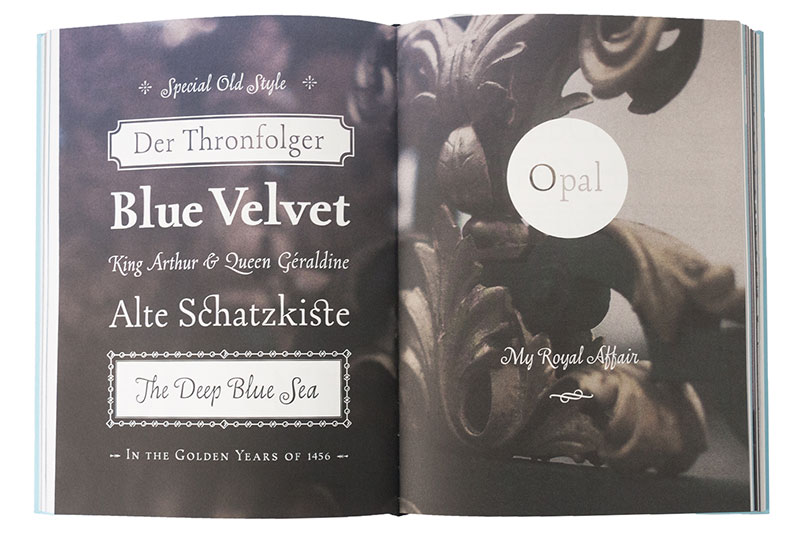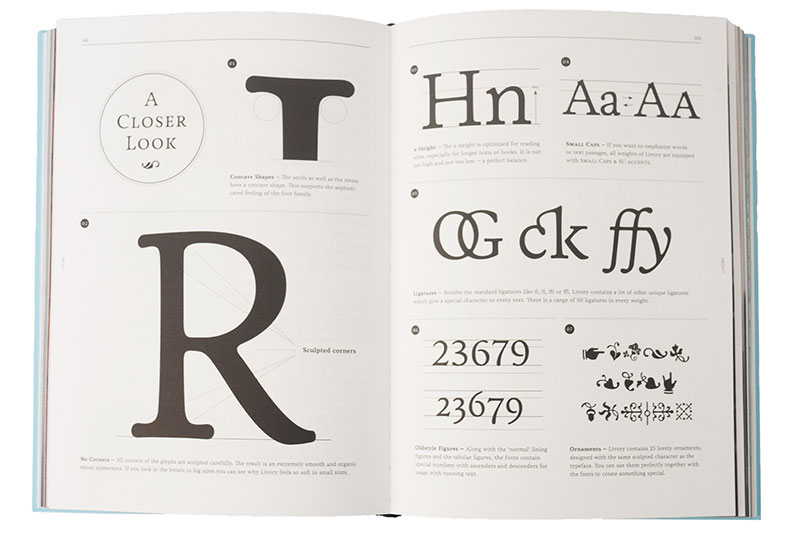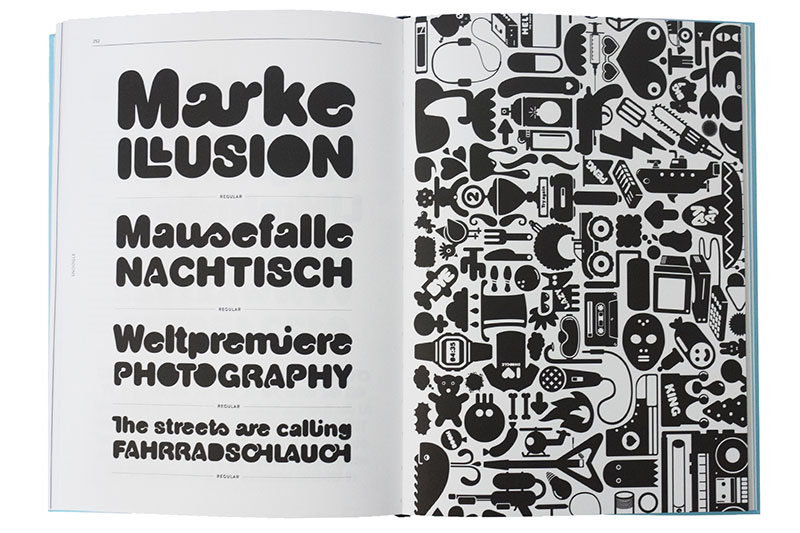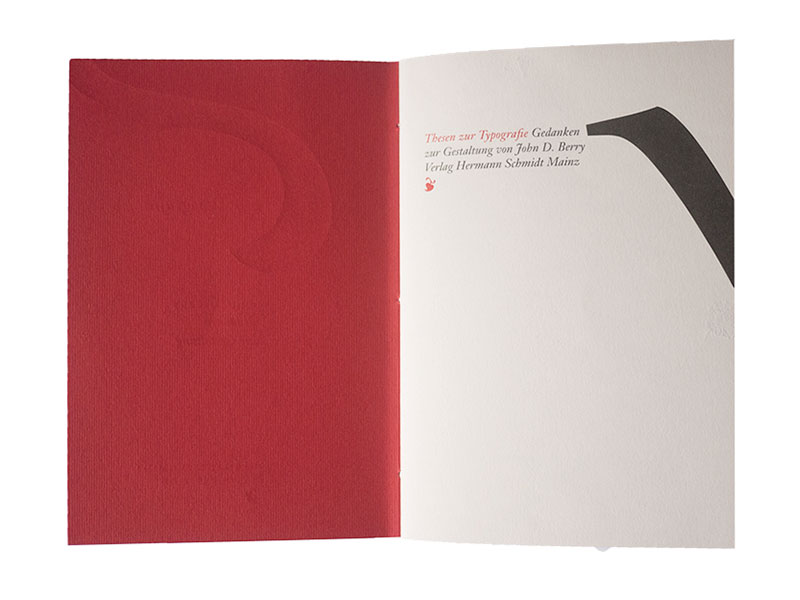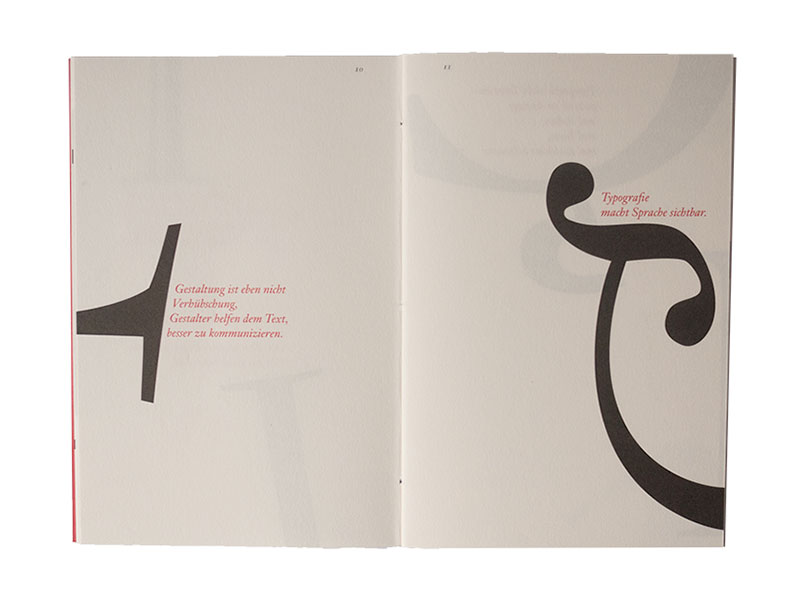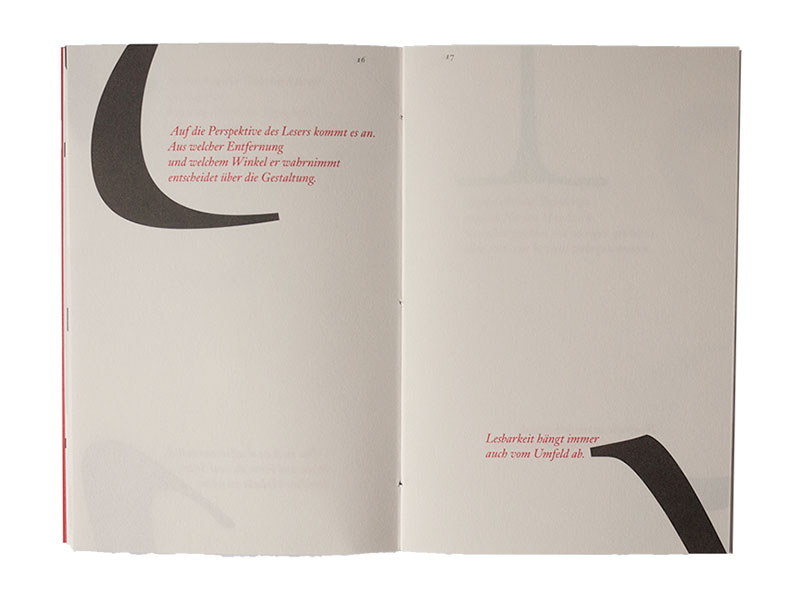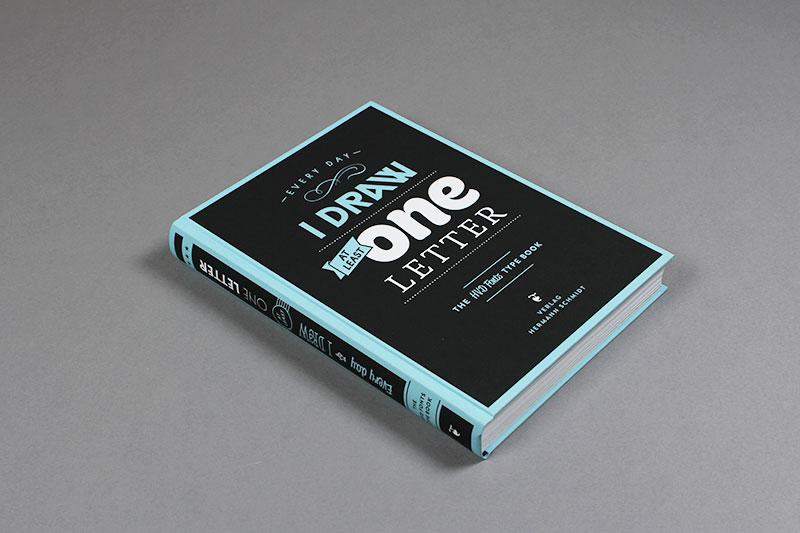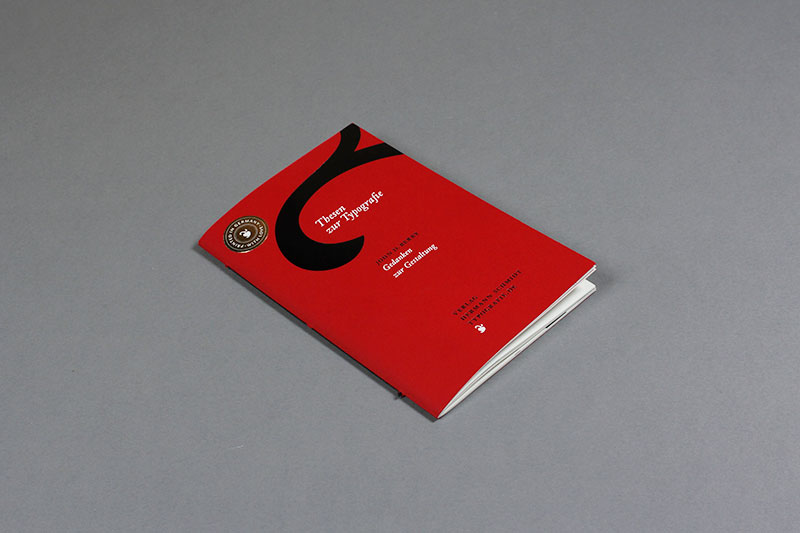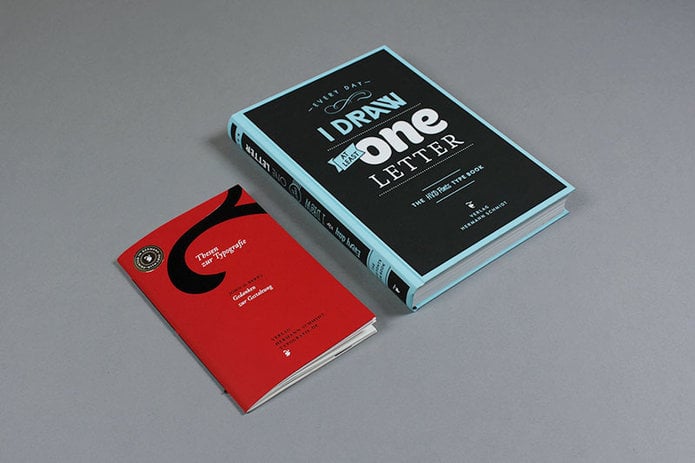
Der Verlag Hermann Schmidt Mainz hat ganz frisch zwei neue Bücher rund ums Thema Schrift veröffentlicht. »I draw at Least One Letter« präsentiert eindrucksvoll die in den letzten 6 Jahren entstandenen Schriften von Hannes von Döhren, der seinen Traum als Schriftgestalter lebt. »Thesen zur Typografie« zeigt liebevoll gestaltete Statements zum Thema Schriftgestaltung und Komposition. Diese zwei lesenswerten Bücher wollen wir euch natürlich nicht vorenthalten und genauer vorstellen.
Every Day I Draw at Least One Letter. The HVD Fonts TYPE BOOK
Erik Spiekermann hat den Eindruck, in Berlin gäbe es derzeit mehr Typedesigner als Polizisten, keine guten Voraussetzungen also, um als Schriftentwerfer den Schritt in die Selbständigkeit zu wagen. Und doch tat Hannes von Döhren vor sechs Jahren genau das. Er beschloss, sich von nun an voll auf den Entwurf von Fonts zu konzentrieren, jeden Tag mindestens einen Buchstaben zu zeichnen, Schrift zum Mittelpunkt seines Lebens zu machen. Und der Erfolg gibt ihm Recht. Die Brandon war der erste Bestseller. Digitale Vertriebswege, im Idealfall die eigene Foundry, erleichtern die Vermarktung, social media die Marketingkommunikation. Vor allem aber tragen leidenschaftliche Begeisterung, beharrliches Dranbleiben, ständige Beobachtung und reger Austausch mit Fachleuten. Kooperation statt Konkurrenz. Lust auf Schrift, statt Schielen auf Zahlen. Und so wurde Hannes von Döhrens Traum wahr, er lebt nicht nur für seine Schriften, sondern auch davon.
In diesem Buch stellt er die Schriften der letzten 6 Jahre vor, 16 Brotschriften, 15 Displayfonts, 31 Familien, 358 Einzelfonts. Er verrät seine Erfolgsgeheimnisse und wie man mit Sprayerschriften umgeht. Erik Spiekermann; Jan Middendorp und Livius Dietzel ergänzen in lesenswerten Artikeln und am Ende des Buches findet der stolze HvD-Font-Buch-Besitzer den Schlüssel zum Glück: Fünf HvD-Fonts for free!
Every Day I Draw at Least One Letter. The HVD Fonts TYPE BOOK
Gestaltung: Hannes von Döhren
Herausgeber: Hannes von Döhren
Verlag: Hermann Schmidt Mainz
Thesen zur Typografie. Gedanken zur Gestaltung
Manchmal sollte man Mac und Maus beiseite schieben – und einfach einen Moment darüber nachdenken, was wir als Gestalter eigentlich tun? Dann fällt Ihr Blick vielleicht ab jetzt auf das liebevoll gestaltete Büchlein mit Gedanken zur Gestaltung von John D. Berry, dem Ehrenpräsidenten der ATypI und Herausgeber von Upper & lower case. Als Mensch des Wortes und der Gestaltung ruft er uns Thesen zur Typografie zu und mahnt: »Inhalt und Form sind einfach zwei Seiten derselben Münze. Nur zusammen betrachtet ergeben sie Sinn.«
John D. Berry sammelt Statements zur Typografie. Den wichtigsten stellt er stark vergrößerte Details unterschiedlichster Serifen zur Seite. Liebevolle Kompositionen, mit denen er Gedanken anstößt - und das Augenmerk des Lesers gleichzeitig aufs Detail lenkt. »Da könnten meine Studierenden je eine These als Grundlage eines Entwurfes nutzen« rief eine Professorin. »Das würde ich gern auf deutsch verlegen« rief Bertram, nachdem John ihm ein Exemplar des Büchleins zu Weihnachten geschickt hatte. Und hier ist nun Ihr Weihnachtsgeschenk an Kollegen, Freunde – und vielleicht an Sie selbst …
Thesen zur Typografie. Gedanken zur Gestaltung
Herausgeber: John D. Berry
Verlag: Hermann Schmidt Mainz